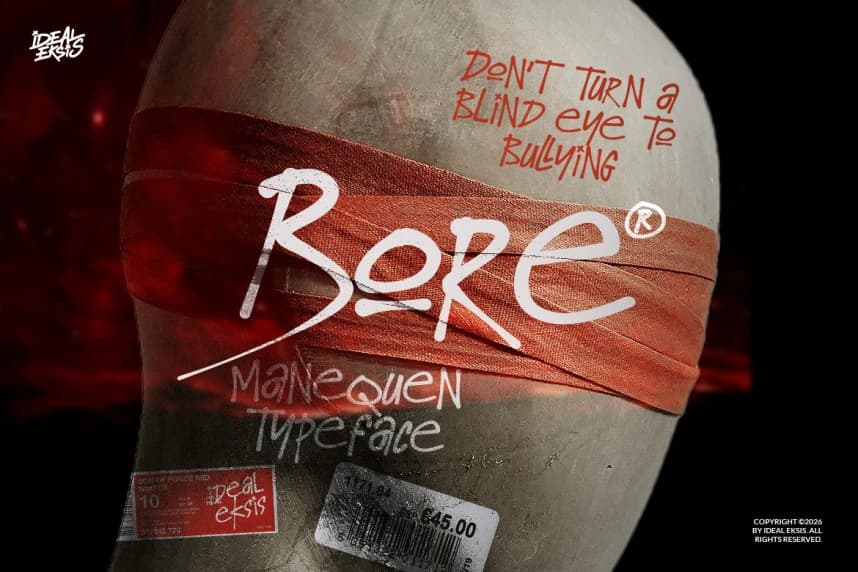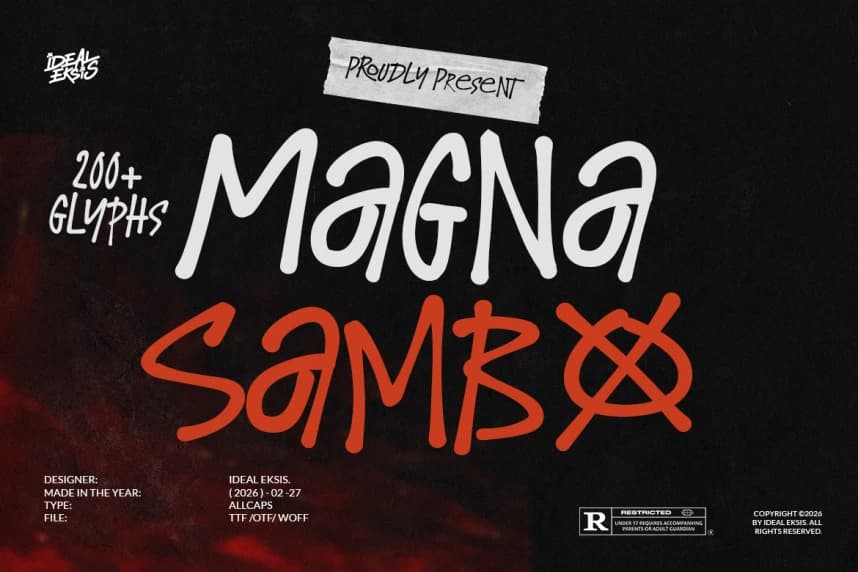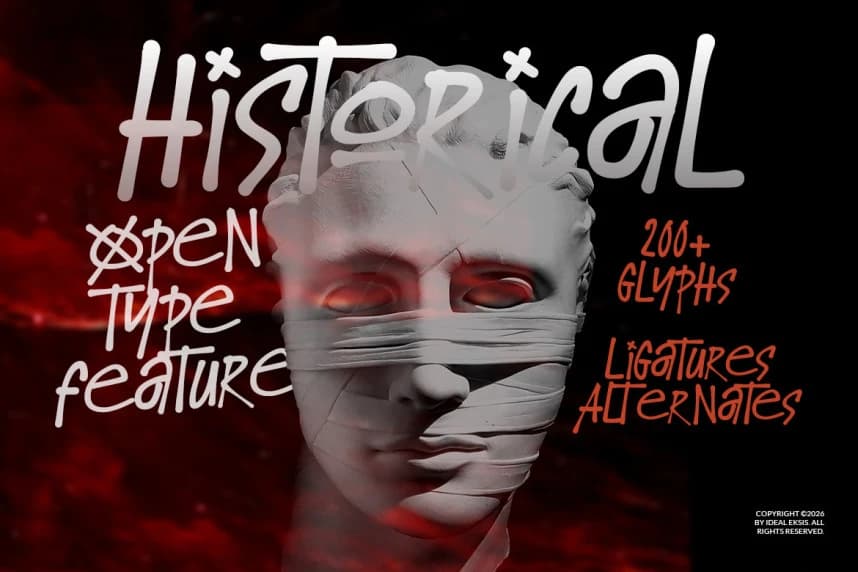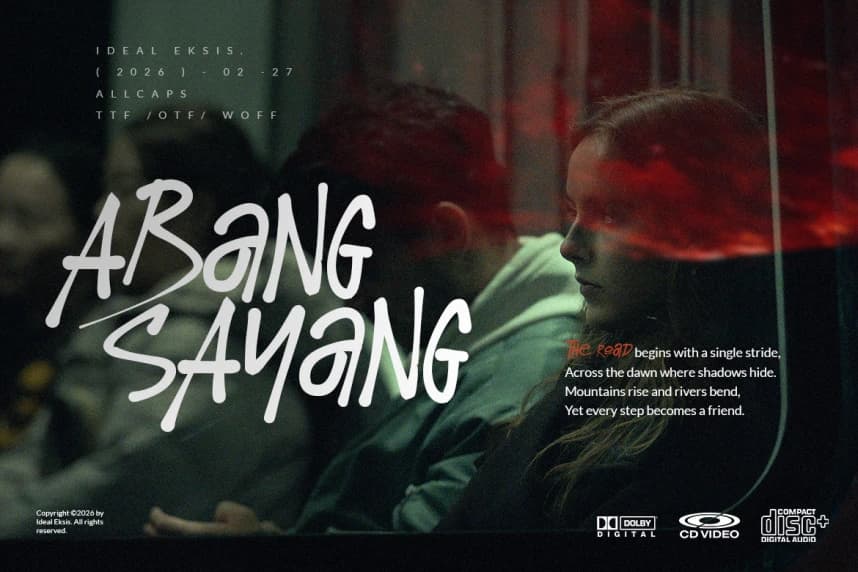
Magna Sambo Font, sokak sanatının ham enerjisini ve marker kaligrafisini yakalayan cesur, ifade gücü yüksek bir yazı tipidir. Harf biçimleri, yuvarlatılmış uçlarla birlikte kalın ve tekdüze vuruşlarla karakterizedir; bu, geniş uçlu bir kalıcı marker kullanıldığını düşündürür.
Magna Sambo Font, sokak sanatı ve marker kaligrafisinin ham enerjisini yakalayan cesur, ifade gücü yüksek bir yazı tipidir. Harf biçimleri, kalın, tekdüze çizgilere ve yuvarlatılmış uçlara sahiptir; geniş uçlu kalıcı bir marker kullanıldığını ima eder.